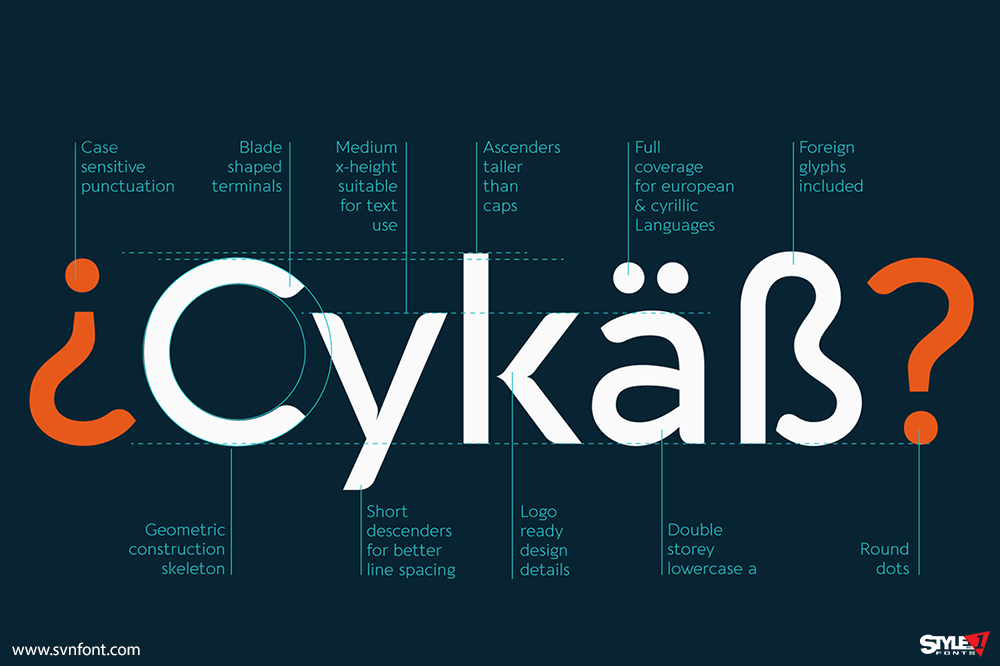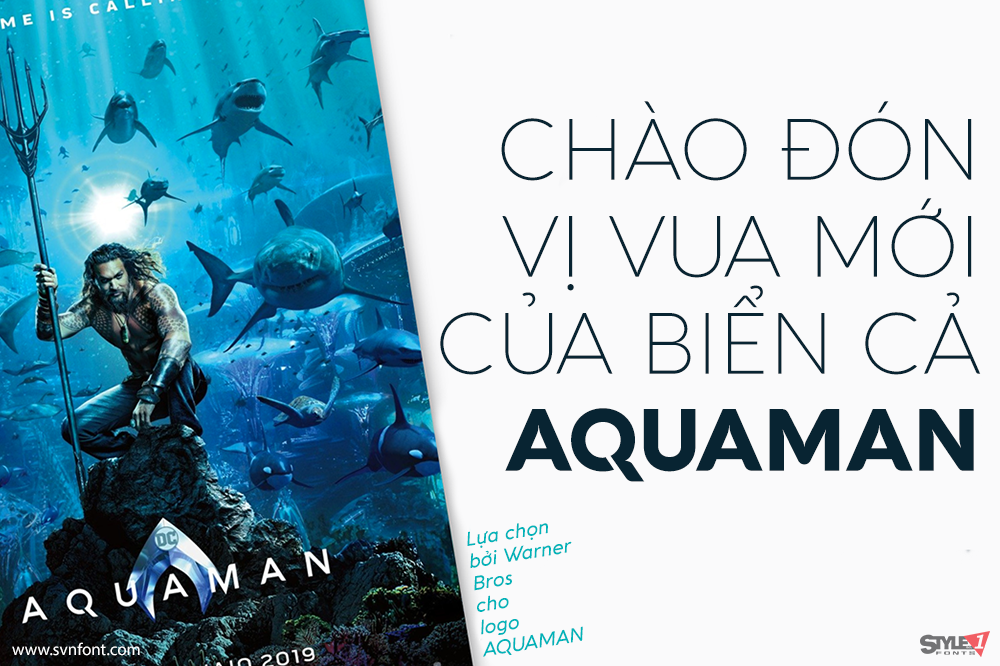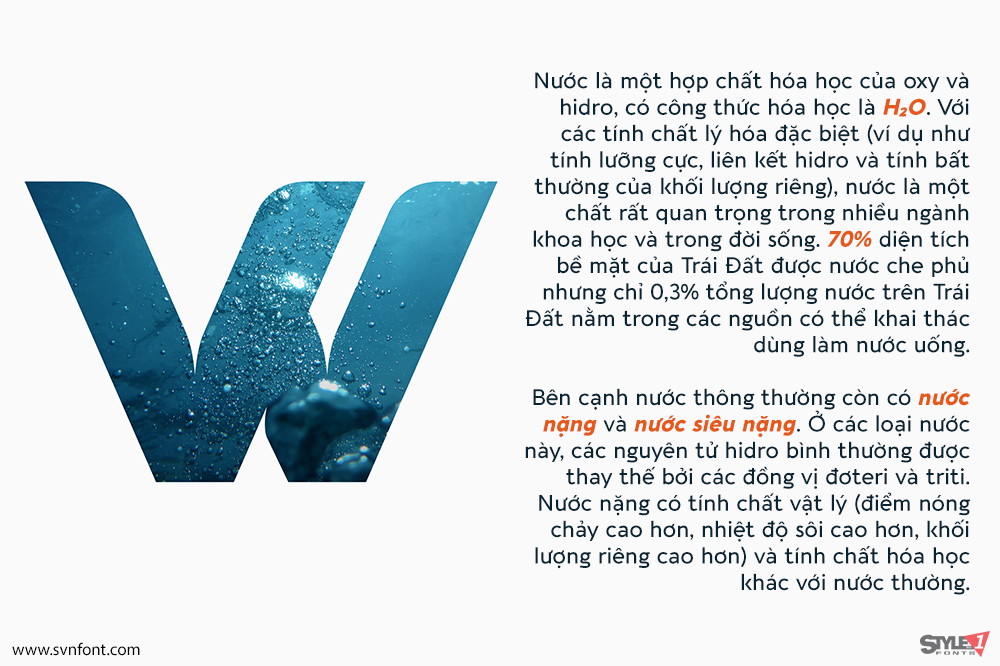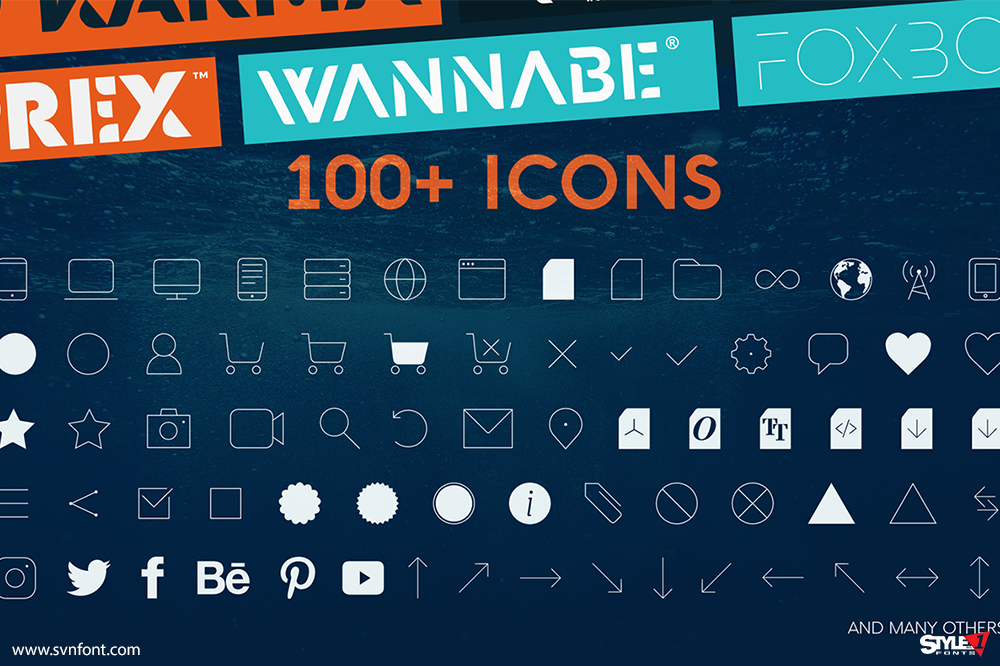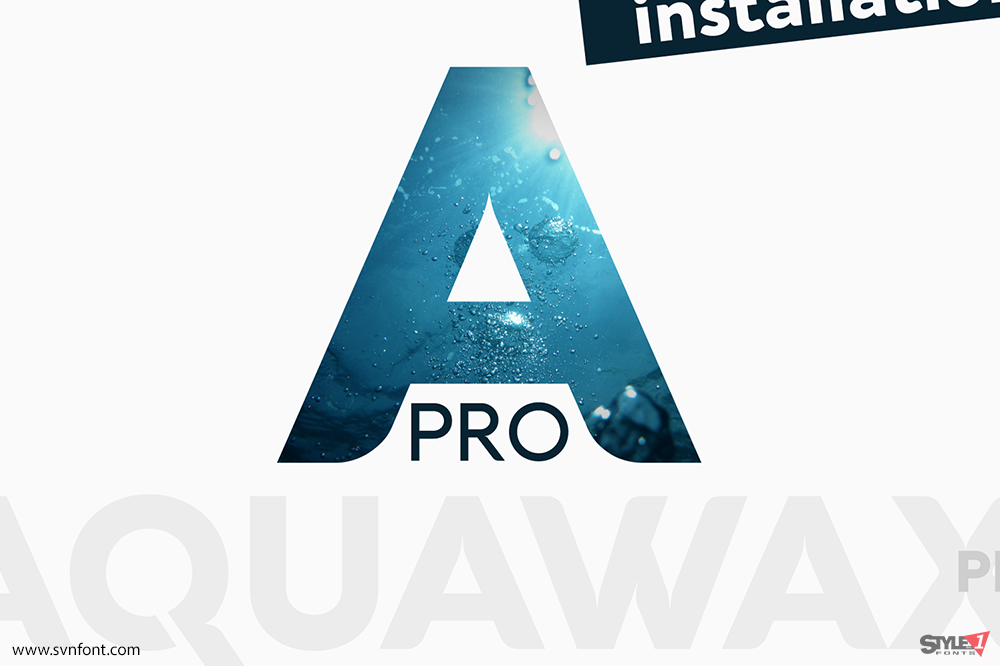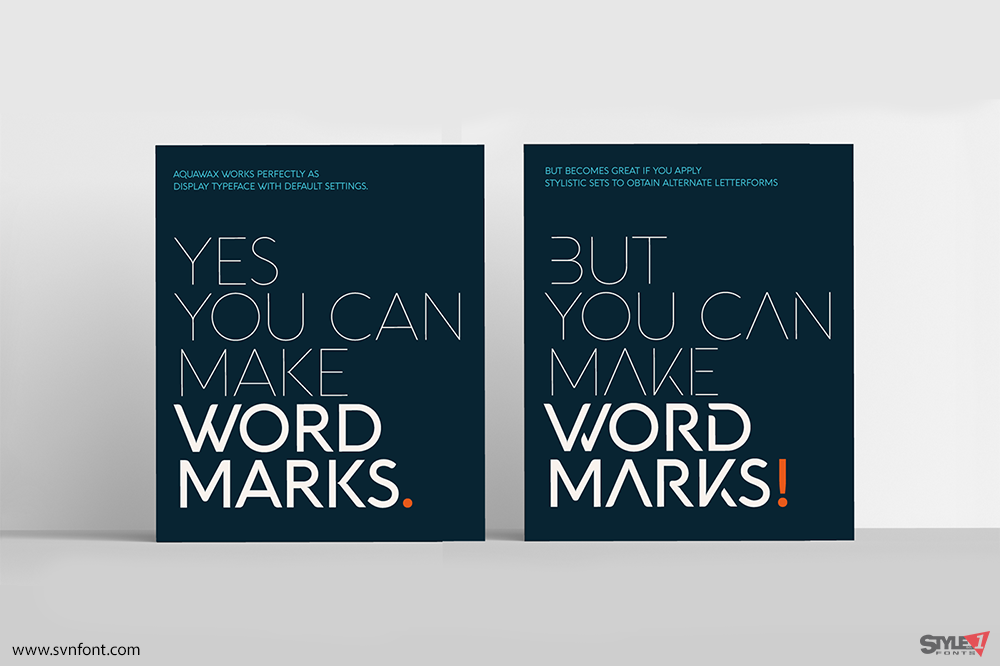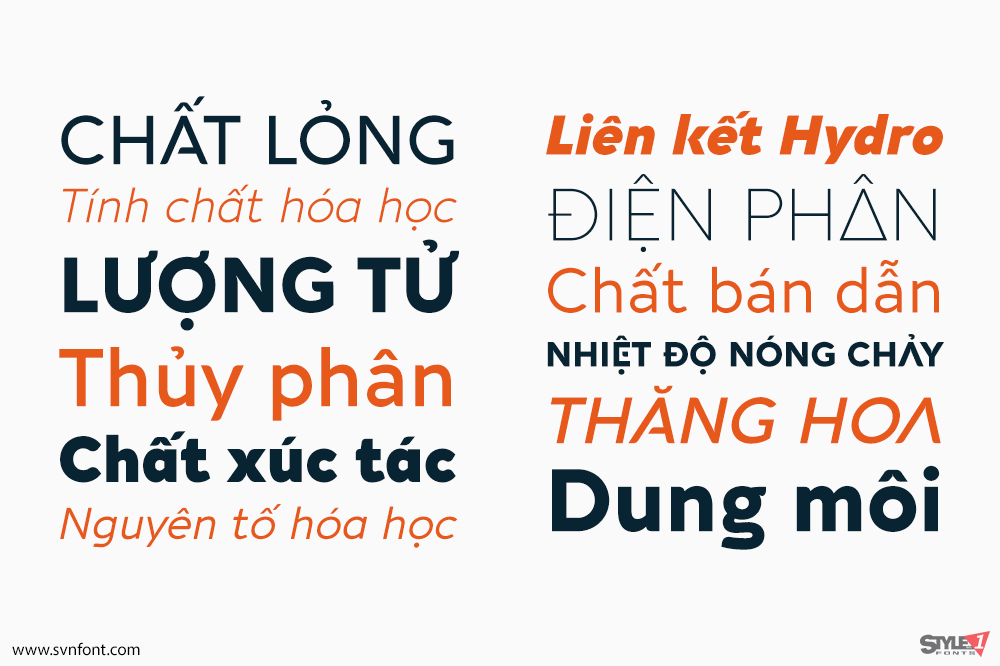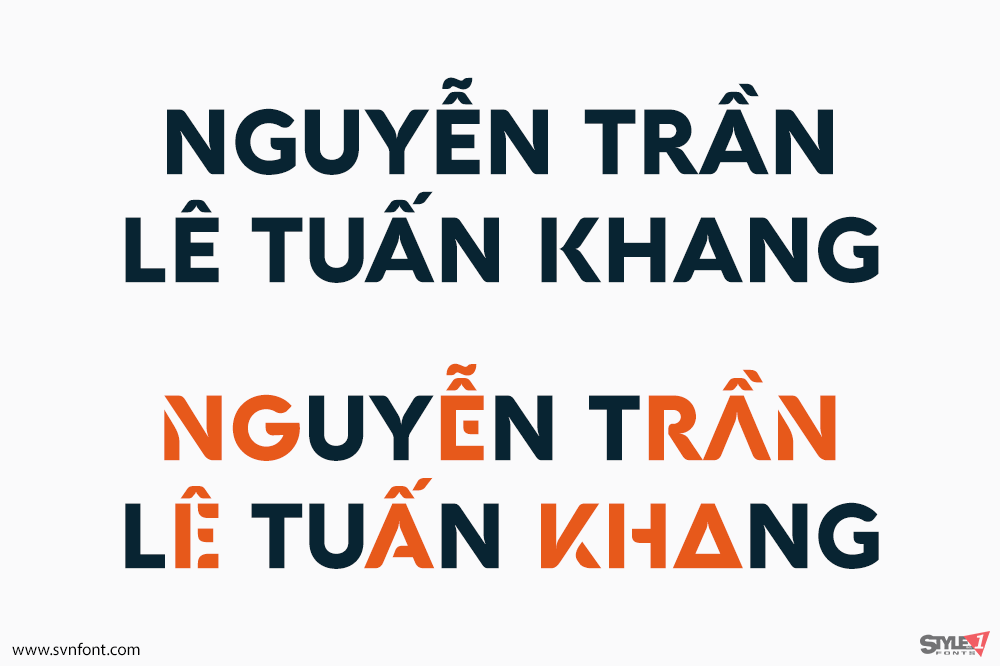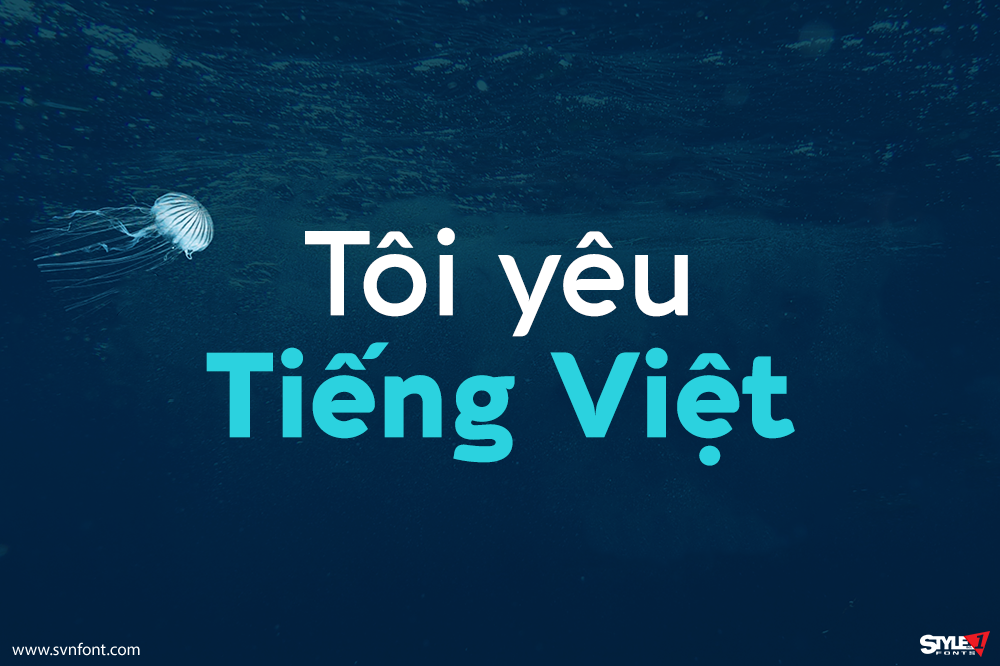
Được Francesco Canovaro tạo ra vào năm 2008 như một phông chữ thương hiệu tùy chỉnh, Aquawax Pro là một trong những kiểu chữ thành công nhất của Zetafonts – đã được Warner Bros chọn để thiết kế logo cho bộ phim Aquaman. Nguồn gốc thiết kế logo của nó thể hiện rõ qua các chi tiết như phần đuôi hình lưỡi kiếm của chữ Q, chân phải hình vây cá của chữ K và chữ W viết hoa bị đảo ngược một cách có chủ ý, cũng như các cạnh bo tròn làm mềm mại các hình dạng chữ theo phong cách hiện đại. Mặc dù những chi tiết này khiến phông chữ cực kỳ phù hợp cho thiết kế logo và hiển thị, đặc biệt ở các độ đậm hơn, nhưng các hình dạng chữ mở, hình học và chiều cao x-height rộng rãi làm cho nó rất dễ đọc ở kích thước nhỏ, trở nên hoàn hảo cho văn bản chính và sử dụng trên web.
Năm 2019, bộ phông chữ này đã được đội ngũ Zetafonts thiết kế lại hoàn toàn, mở rộng bộ ký tự gốc để bao gồm chữ Cyrillic và Hy Lạp, đồng thời thêm ba độ đậm và kiểu nghiêng vào sáu độ đậm ban đầu, tổng cộng có 27 độ đậm (bao gồm 9 ký hiệu). Phiên bản được khôi phục và cải tiến, mang tên Aquawax Pro, cũng bao gồm đầy đủ các tính năng Open Type cho Số vị trí (Positional Figures), Ký tự thay thế theo phong cách (Stylistic Alternates), Chữ ghép tùy chọn (Discretionary Ligatures) và Chữ in hoa nhỏ (Small Caps), và bổ sung các hình dạng ký tự thay thế mới có thể truy cập dưới dạng Ký tự thay thế theo phong cách. Được tối ưu hóa để dễ đọc tối đa trên màn hình, nó hỗ trợ hơn 200 ngôn ngữ sử dụng bảng chữ cái Latinh, Cyrillic và Hy Lạp, với đầy đủ các dấu và dấu phụ.